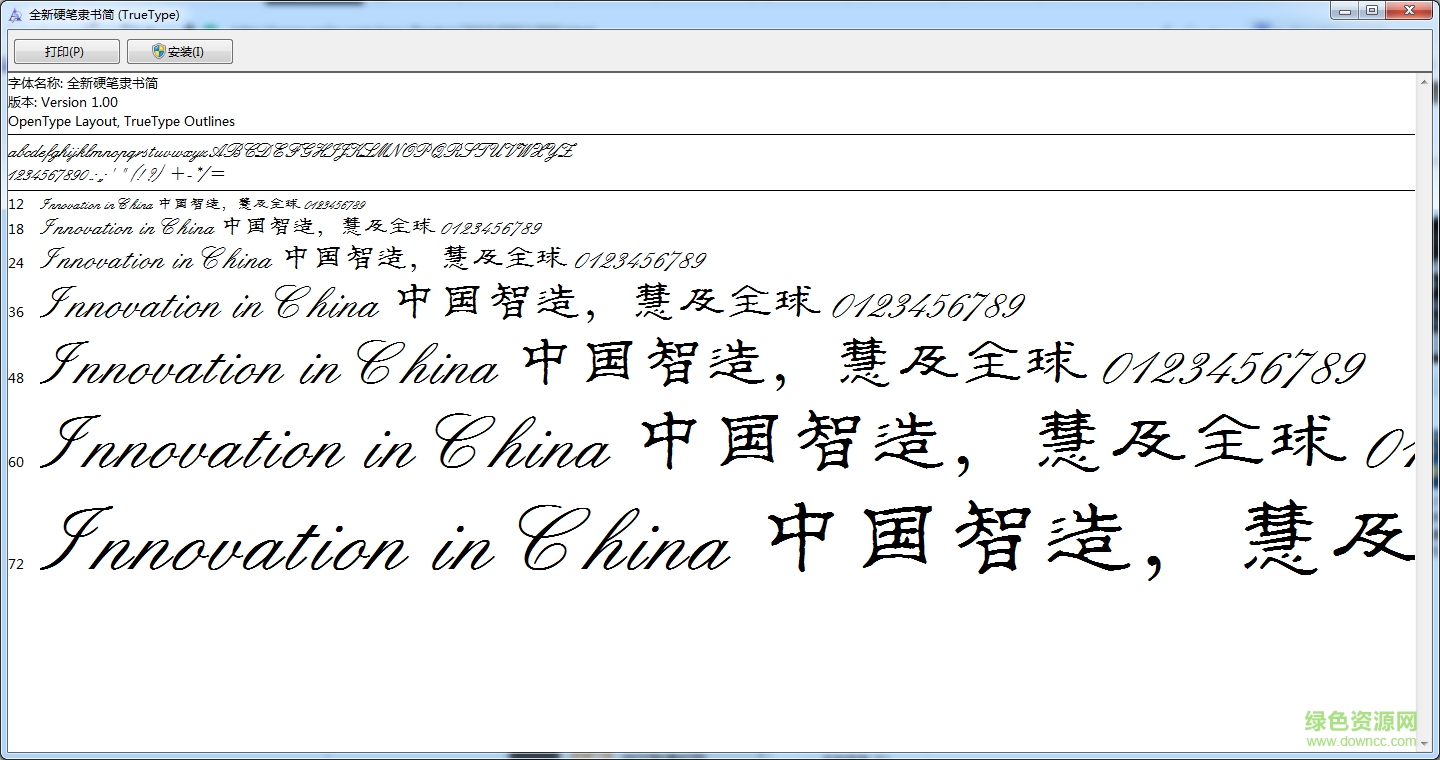
qxyingbili字體就是全新硬筆隸書簡,這款隸書比起常見的方正隸書和華文隸書要更細(xì)更長一些,結(jié)構(gòu)上多了一點(diǎn)變化,精巧美觀,同時也更加具有實(shí)用性,歡迎下載!
隸書基本是由篆書演化來的,主要將篆書圓轉(zhuǎn)的筆劃改為方折,因?yàn)樵谀竞喩嫌闷釋懽趾茈y畫出圓轉(zhuǎn)的筆劃,所以隸書的書寫速度更快。
線條由篆書委婉的弧筆變?yōu)殡U(xiǎn)峻的直筆,曲折處由篆書的聯(lián)綿圓轉(zhuǎn)變?yōu)檗D(zhuǎn)折的方筆。隸變標(biāo)志著漢字相形性的破壞和抽象符號的確立,使?jié)h字由古文字體系向今文字體系轉(zhuǎn)換;同時也標(biāo)志著隸書的獨(dú)立品格和美學(xué)特征的最終形成。